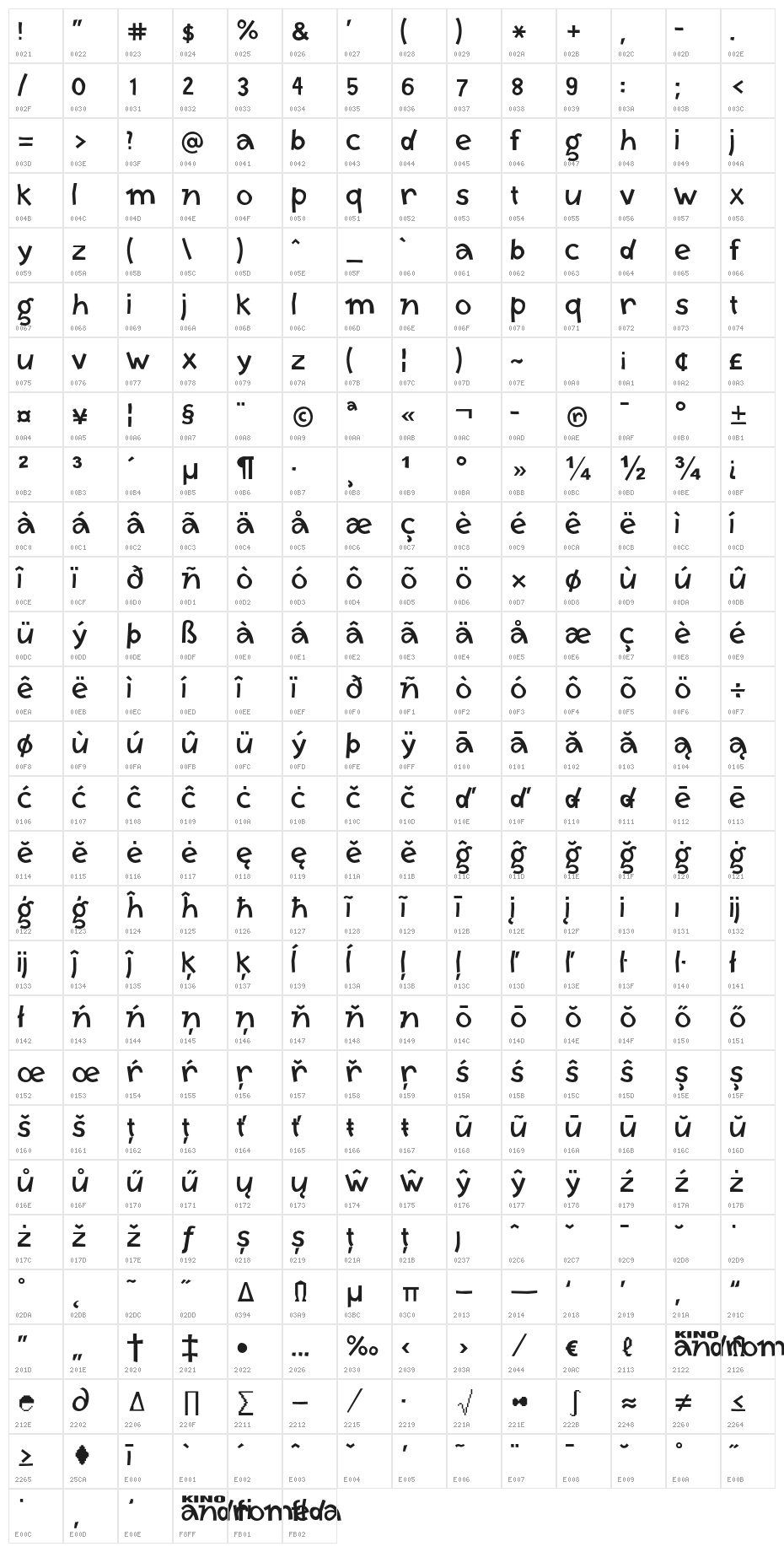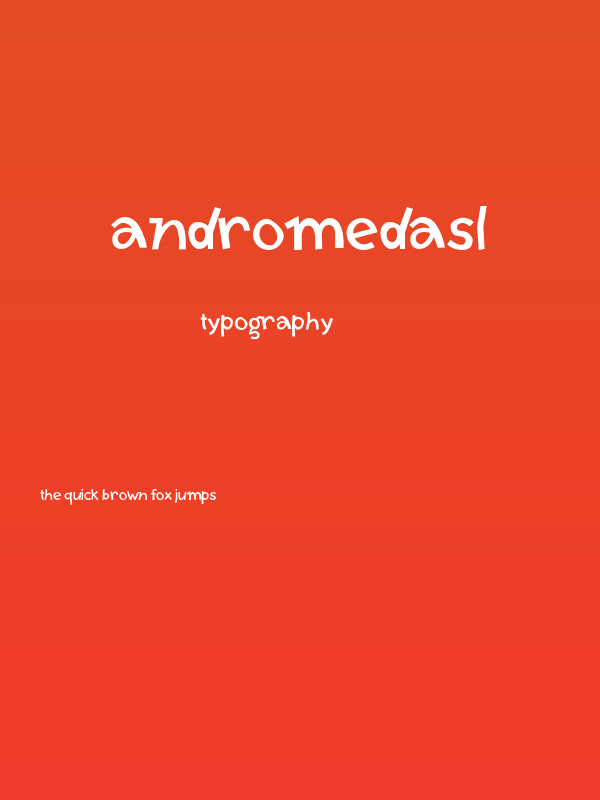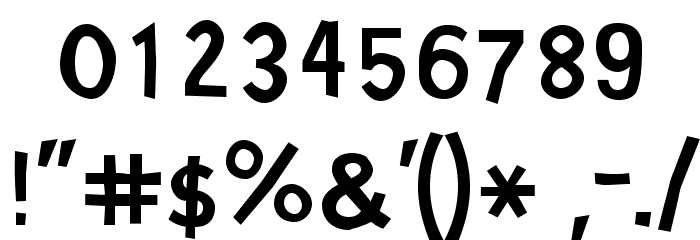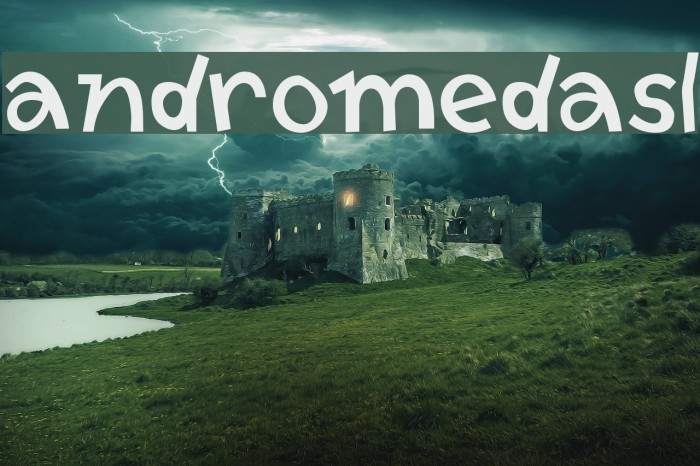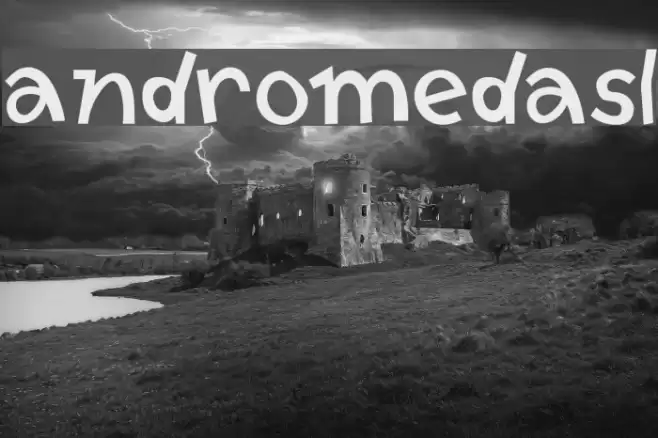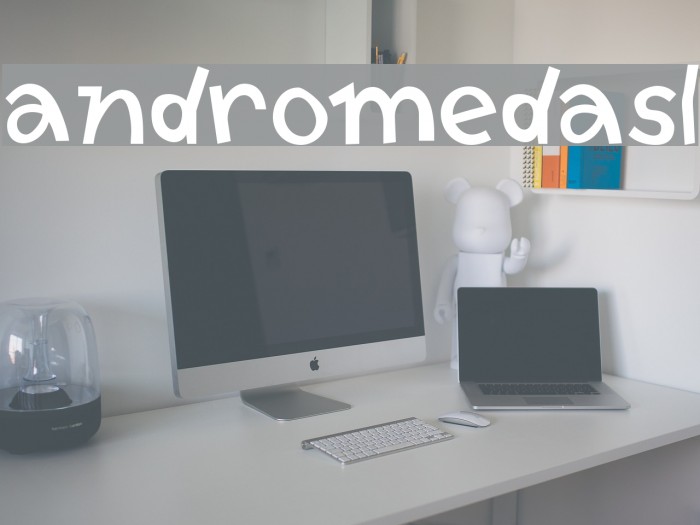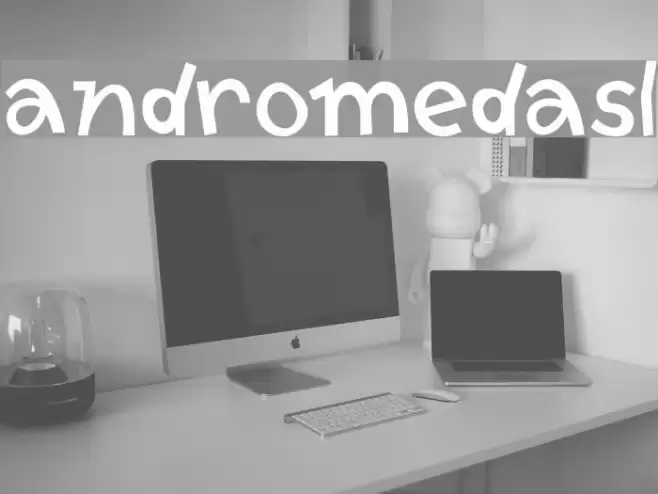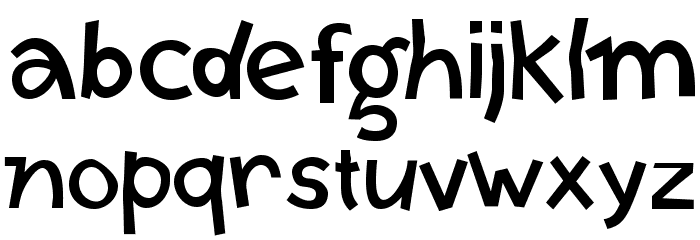
AndromedaSL Font
| الاسم | AndromedaSL |
| الإصدار | Version 2.001 2006 by Silesian Letters |
| النمط العام | Playful, Whimsical |
| حالة الاستخدام | Headlines, Logos, Creative projects |
| مشاريع مقترحة | Ideal for children's books, greeting cards, playful branding, and creative posters. |